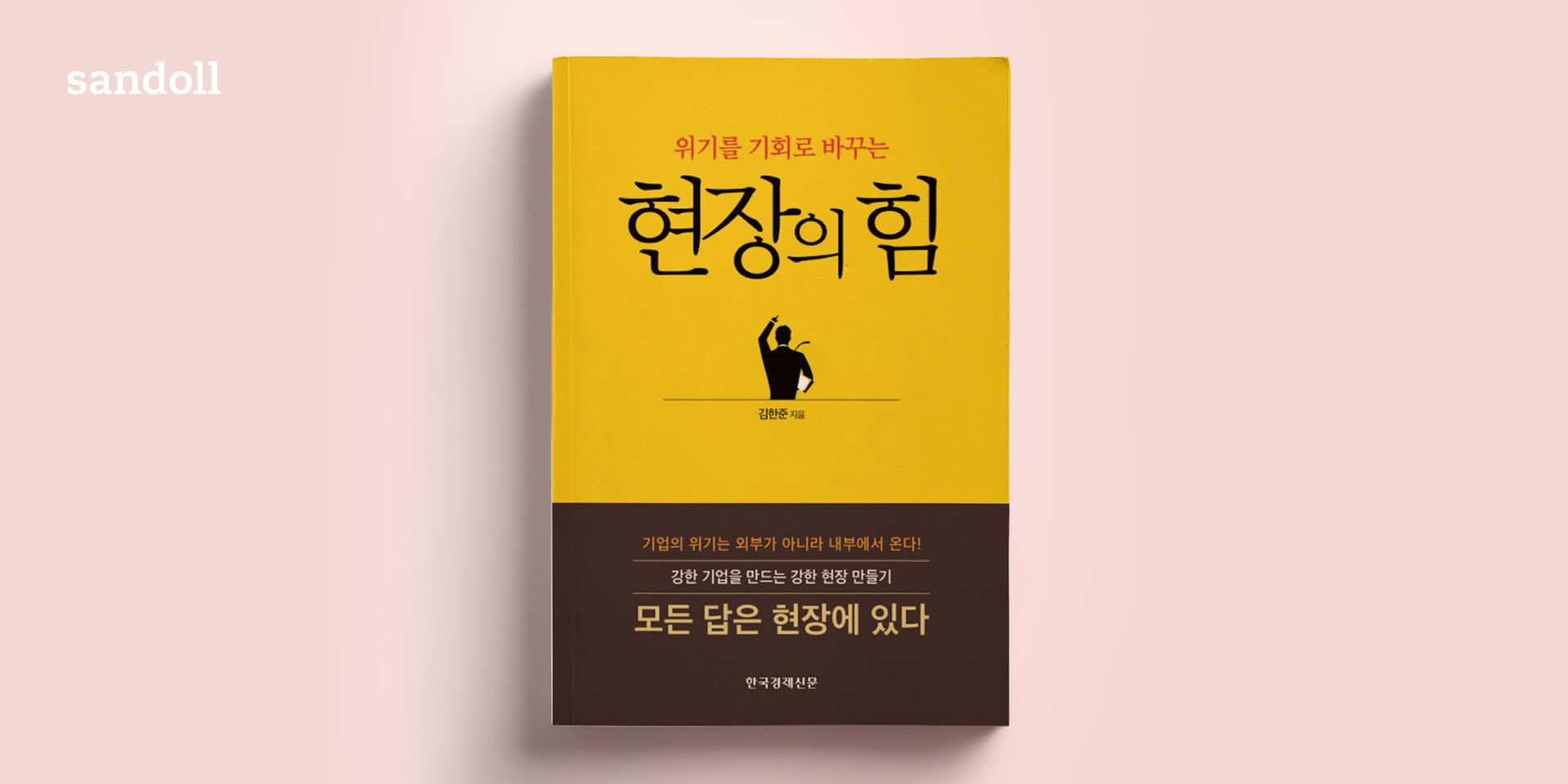
Sandoll 명조Neo1
산돌 명조Neo1은 다양한 웨이트의 슈퍼 패밀리를 갖춘 프리미엄 명조 폰트이다.산돌의 기술과 경험을 집약한 프리미엄 본문서체 Sandoll Neo Series의 첫 명조 폰트로서 기존 산돌 명조의 고전적인 모습에서 현대적인 세련됨이 돋보이도록 디자인하였으며 명조체 특유의 돌기를 우아하면서 부드럽고 절도있게 표현했다.